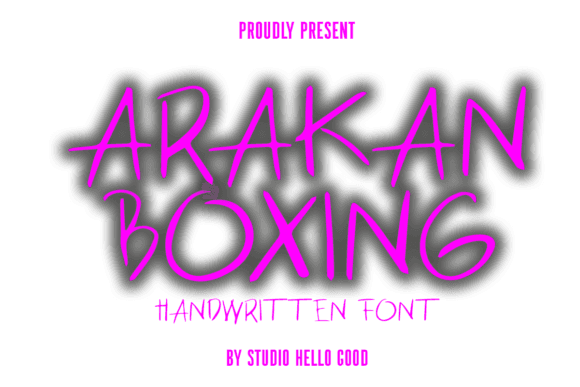
Apresentamos Arakan Boxing – uma fonte manuscrita ousada e distinta que canaliza a força bruta e o espírito do boxe tradicional. Criada com uma combinação única de autenticidade e talento artístico, esta tipografia não é apenas uma celebração visual do esporte, mas também um testemunho da maestria da caligrafia desenhada à mão.